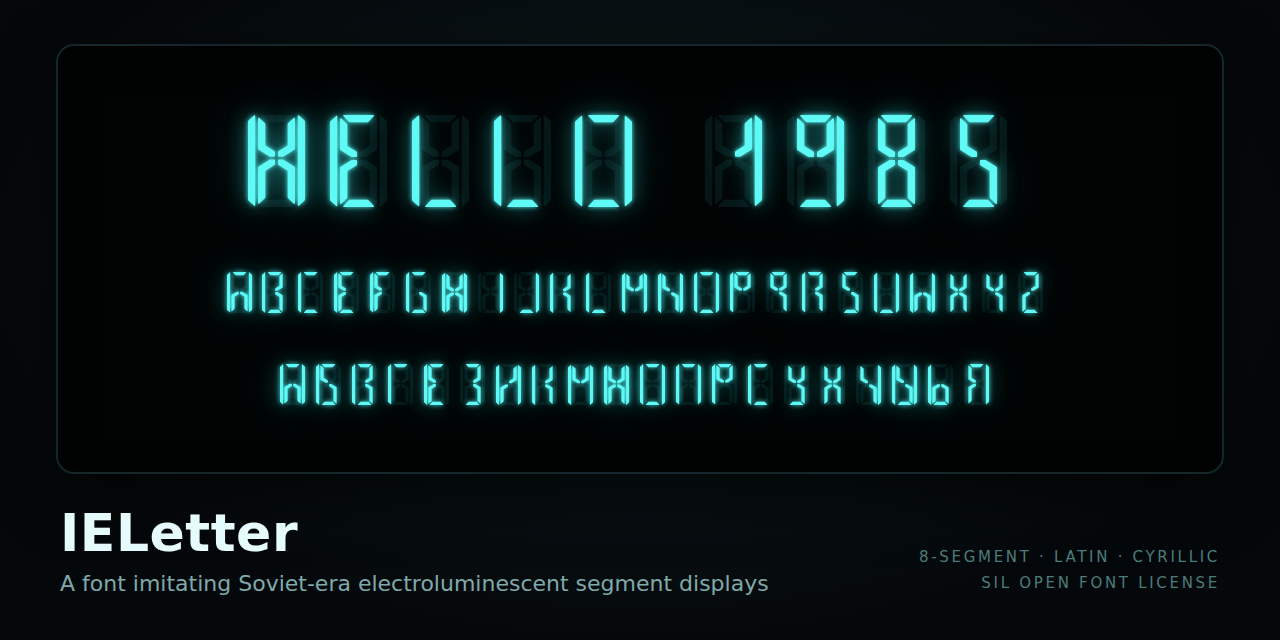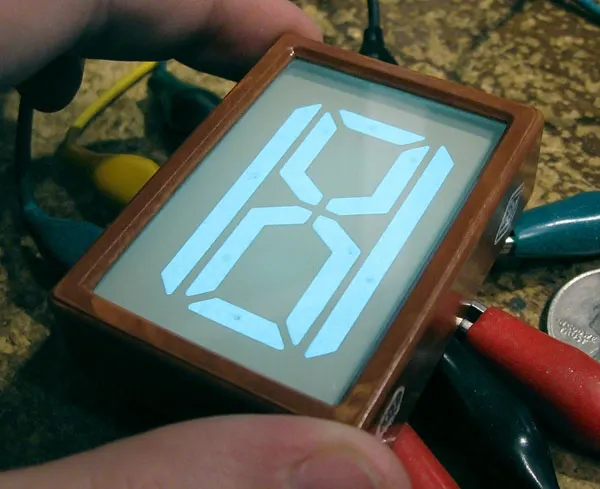
ラテン文字・数字とキリル文字の見本です。画像ではなく Web フォントなので、文字を書き換えて試せます。
IEL-0-VI とは
IEL-0-VI(ИЭЛ-0-VI)は、旧ソ連で使われていたセグメント式の EL(エレクトロルミネセンス)ディスプレイです1。1980年代のソ連で、軍用に作られたものとされています2。
見た目は蛍光表示管(VFD)に似ていますが、仕組みは大きく異なります。真空管ではなく、ヒーター(熱陰極)もありません。蛍光体を混ぜた樹脂を、導電層と酸化スズのガラス窓ではさんでコンデンサーのような構造にし、高電圧の交流で充放電を繰り返すことで発光します2,1。駆動には約 200V・400Hz の交流が必要です1。
特徴的な 8セグメントの配置で、「T」を除くほぼすべてのキリル文字とラテン文字を表現できるとされています2,1。下の写真は、すべてのセグメントを点灯した状態です。斜めのセグメントを組み合わせた配置が分かります。
IELetter 8A
EL ディスプレイ「IEL-0-VI」を模したフォントです。
IEL-0-VI で各文字をどのセグメントの組み合わせで表示するかは分かっていません。Ver.0.1 は、それらしいパターンを作れた文字にだけグリフがあります。
ラテン文字の小文字は、大文字とは別の形で 8文字を収録しています。